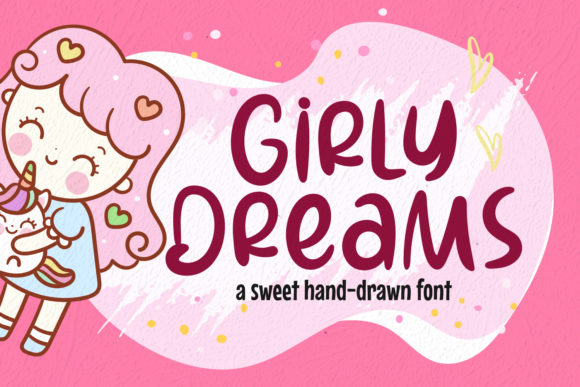
Girly Dreams
Trouver les bons éléments de conception peut être un défi, mais Girly Dreams propose une collection exceptionnelle qui rehausse instantanément votre travail.
Que vous créiez des produits POD (impression à la demande), des invitations de mariage ou des visuels pour les réseaux sociaux, Girly Dreams est un choix idéal.